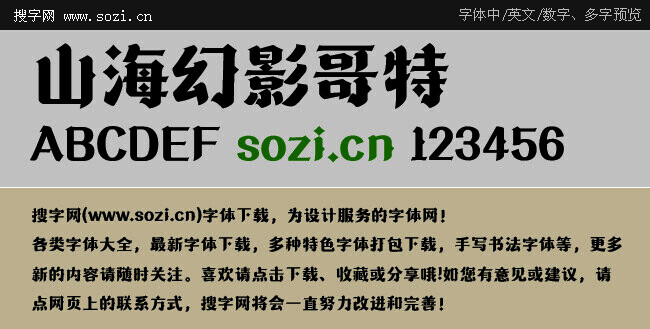
山;糜案缣
搜字網(wǎng)提供一款山;糜案缣刂形乃囆g(shù)字體下載,該字體融合了西方哥特元素,字體獨特,新穎華麗。漢字藝術(shù)與西方文字的融合,如夜空中閃爍著暗黑光芒;個性鮮明的字體特征,散發(fā)著神秘而高冷的氣息。適合包裝設(shè)計、海報設(shè)計、廣告設(shè)計等應(yīng)用。